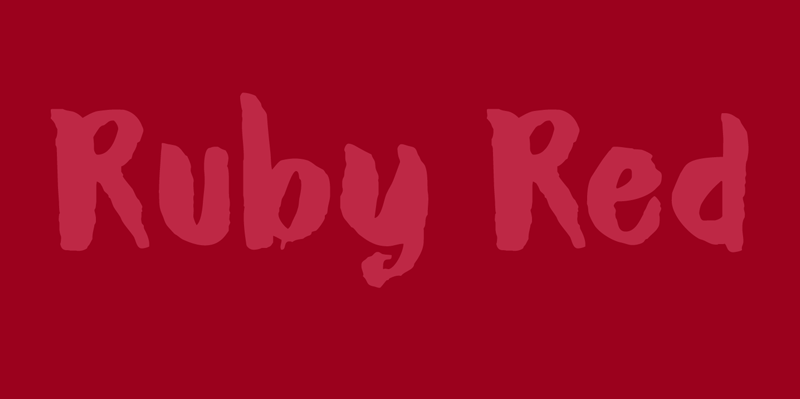
DK Ruby Red font – Fonte Grátis
DK Ruby Red font
A fonte DK Ruby Red é uma escolha incrível para aqueles que buscam um estilo elegante e versátil para seus projetos digitais. Ideal para textos legíveis e atraentes, essa font foi criada por Hamilton com um toque de exuberância em cada letra. Suas linhas curvadas e desenhos arredondados dão ao texto uma aparência romântica que combina bem tanto no design gráfico quanto na tipografia para aplicativos móveis e desktops. A DK Ruby Red é perfeitamente adaptada para textos legíveis de vários tamanhos, proporcionando um equilíbrio entre elegância e sofisticação. Seja você criando uma newsletter envolvente ou estabelecendo a identidade visual de seu site, essa font se destacará com sua aparência suave e impecável. Com seus traços finos e arredondados, DK Ruby Red é perfeita para criar um layout que seja tanto profissional quanto encantador.